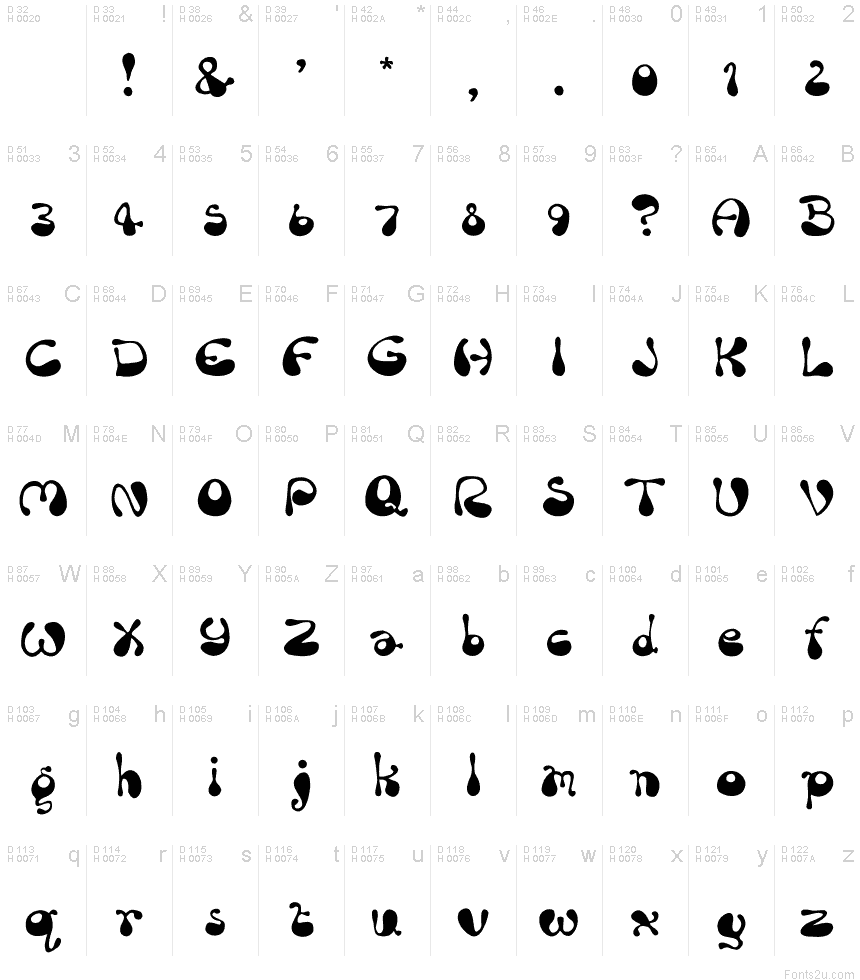
Rum Bubber di Uddi Uddi è un font display gratuito in stile cartoon, con un tocco sbarazzino tipico dei disegni a mano degli anni '90. Le lettere appaiono gonfie e gommose, con forme spesse e fluide, curve asimmetriche e piccoli ganci che rendono il carattere giocoso piuttosto che ordinato.
Si adatta perfettamente a poster per bambini, titoli in stile fumetto, copertine di fanzine, volantini per feste o confezioni di dolci e giocattoli, dove questa silhouette tondeggiante riesce a creare l'atmosfera in un attimo. Essendo un font gratuito, è l'ideale anche per titoli brevi, bozze di loghi e grandi citazioni che richiedono un aspetto stravagante, morbido e inconfondibilmente fatto a mano.